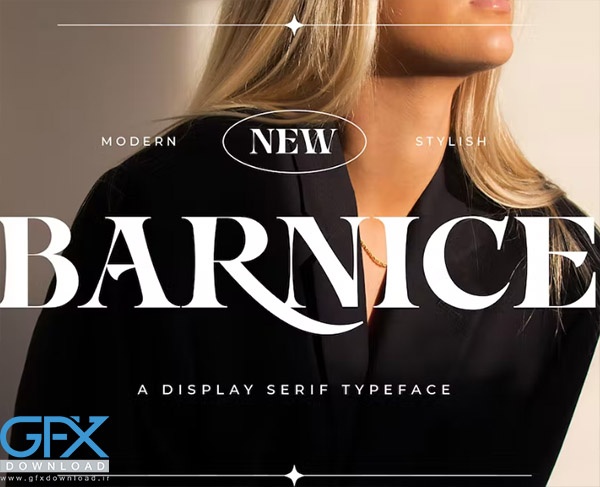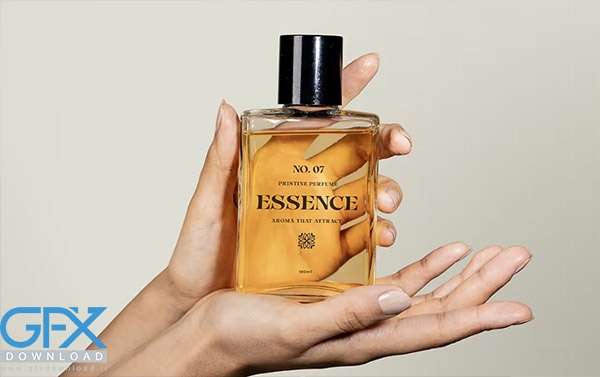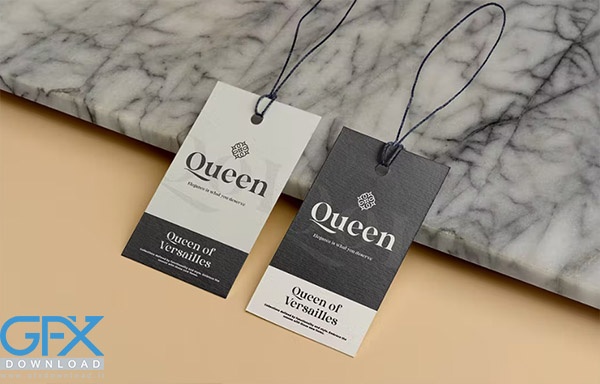
دانلود فونت تبلیغاتی Barnice
فونت تبلیغاتی Barnice
دانلود فونت انگلیسی تبلیغاتی مدرن Barnice
Barnice یک فونت نمایشگر سریف مدرن است. بدون توجه به موضوع، این فونت یک دارایی باورنکردنی برای کتابخانه فونت‌های شما خواهد بود، زیرا این قابلیت را دارد که هر خلاقیتی را ارتقا دهد. برای دانلود فونت تبلیغاتی Barnice از جی اف ایکس دانلود به ادامه مطلب مراجعه کنید. شامل حروف بزرگ – کوچک – نمادها و علائم نقطه گذاری – اعداد – لیگاتور – جایگزین – پشتیبانی چند زبانه و فایل های (OTF، TTF، WOFF، WOFF2).